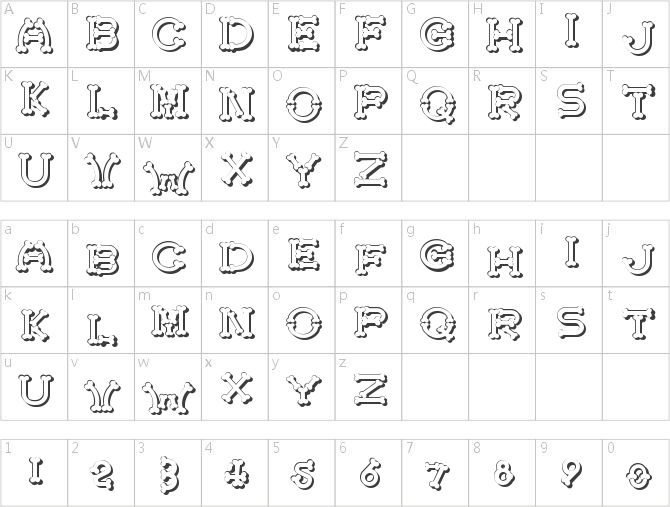
bonecracker_shadow
bonecracker_shadow介紹
bonecracker_shadow字體字庫是一款讓人賞心悅目、百看不厭的英文字體,適合各類廣告和產品包裝設計應用,字體大小0.24MB,格式為ttf字體,上傳用戶是洛洛,作者/版權方為未知
bonecracker_shadow效果圖